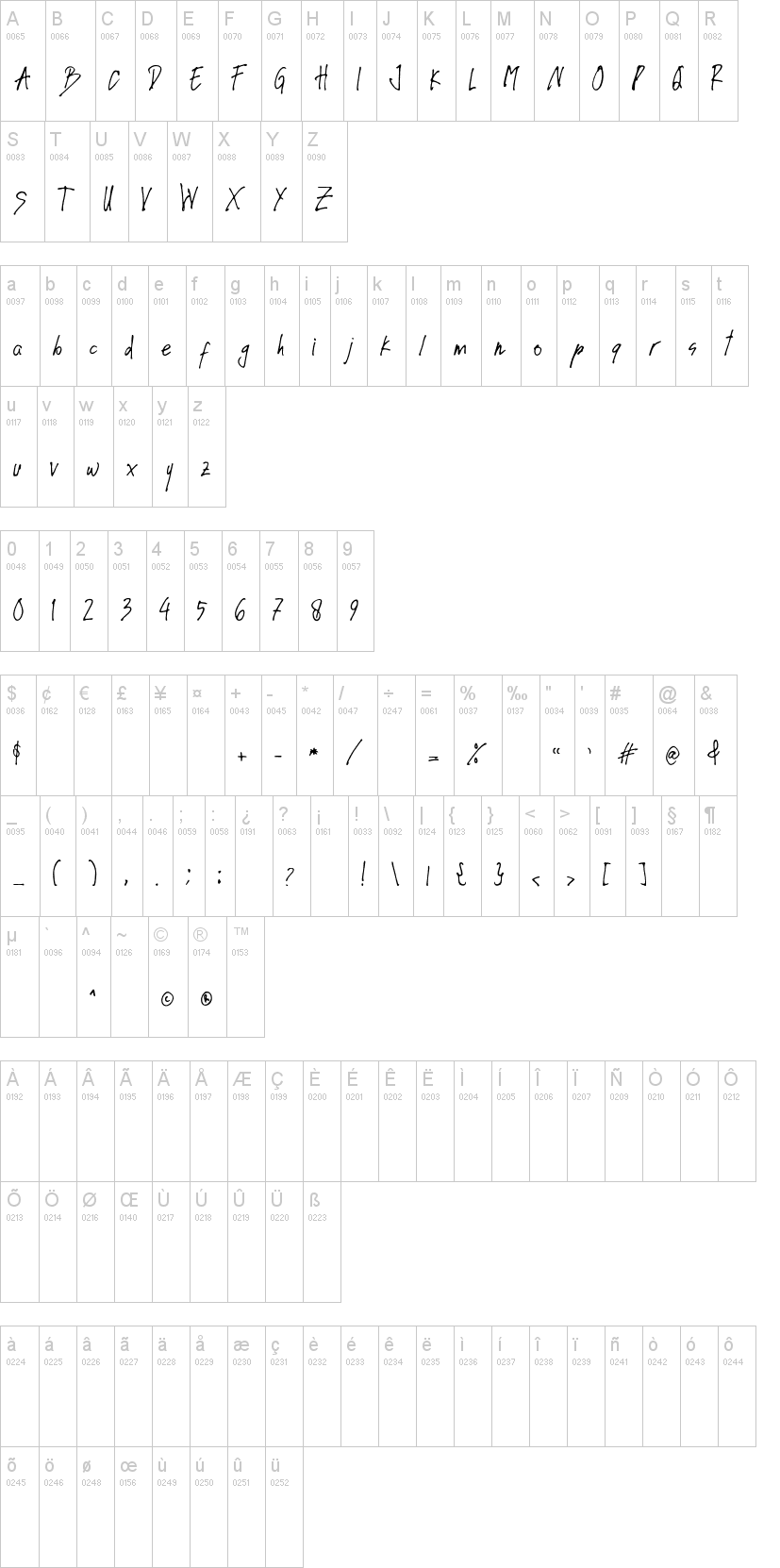
Shady Butter
Shady Butter 是一种手写风格的字体,适用于各种创意设计和印刷品,如海报、名片、标志和包装设计等。它的外观是手写的,有点像涂鸦,但是非常可读,并且非常适合用于各种设计项目。 Shady Butter 字体采用不规则的形状和线条,让它看起来非常有个性,同时在字母之间的空隙处添加了一些自然的空白,使得文本读起来更加流畅和舒适。此外,Shady Butter 字体包含了许多特殊字符和符号,可以帮助设计师实现更具创意的设计。
Shady Butter是一款非常不错的手写艺术字体,具有很好的视觉感,适合于文化类的宣传设计、商业类品牌的广告和产品包装设计以及个性化文字排版等较多场景。
Shady Butter字符映射图